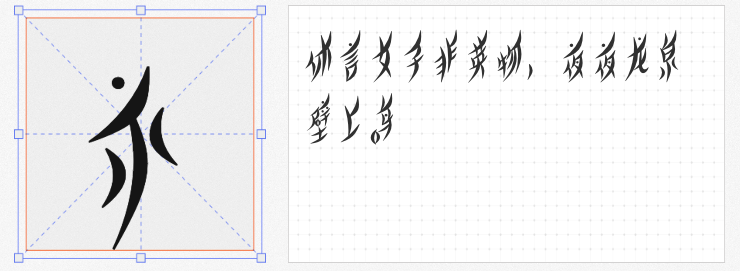
在追求视觉冲击力的设计领域,独特且富有创意的字体不仅是信息的载体,更是情感的表达与氛围的营造者。今天,就为大家揭秘四款风格迥异、灵感来源抽象的免费商用字体,它们将为你的设计作品增添无限可能。
1. 余繁真素体
余繁真素体,一款以直线为灵魂的字体,彻底颠覆了传统字体的书写逻辑。每一个笔画都由简洁的直线构成,没有丝毫多余的修饰,展现出一种纯粹而极致的美学。这种设计不仅考验了设计师的几何构图能力,更赋予了字体一种未来感和科技感,非常适合现代简约风格的设计项目,如科技产品海报、极简主义网站等。
2. 猫啃网故障黑
灵感源自日本瀞之故障黑体,猫啃网故障黑体通过巧妙的数字处理,将思源黑体赋予了故障艺术的灵魂。扭曲的笔画、闪烁的光影效果,仿佛将观者带入了一个充满电子噪点与未来感的赛博空间。这款字体是艺术设计、游戏界面、音乐节海报等领域的理想选择,能够瞬间提升作品的视觉冲击力,营造出强烈的科幻氛围。
3. 也字工厂柳叶体
也字工厂柳叶体,一款以女书文字为灵感的创意字体,不仅是对世界唯一女性文字的致敬,更是对女性话语权与文化抗争精神的颂扬。其笔画流畅如柳叶轻舞,既保留了传统书法的韵味,又融入了现代设计的简洁与灵动。这款字体适合用于女性主题、文化展览、公益广告等场合,传递出温暖而坚韧的力量。
4. 山字瓜子体
源自图文店日常工作的创意火花,山字瓜子体以其圆润可爱的字形设计,成为了广告设计与儿童产品包装的宠儿。虽然大字显示效果更佳,但那份纯真无邪的童趣,足以让任何设计作品瞬间变得生动有趣。无论是卡通形象周边、儿童书籍封面,还是亲子活动海报,山字瓜子体都能完美融入,营造出温馨欢乐的氛围。
这四款字体,每一款都承载着设计师独特的创意与灵感,为设计领域注入了新的活力。不妨在你的下一个项目中尝试使用它们,开启一场视觉与创意的奇妙旅程。